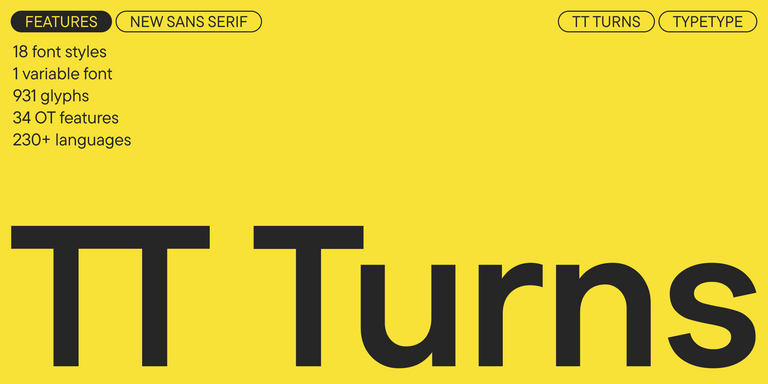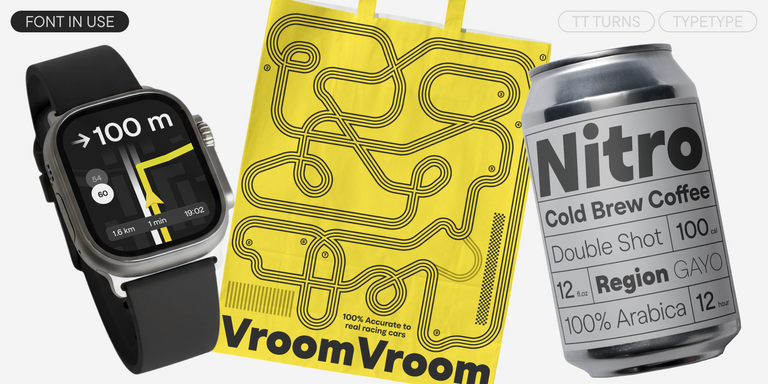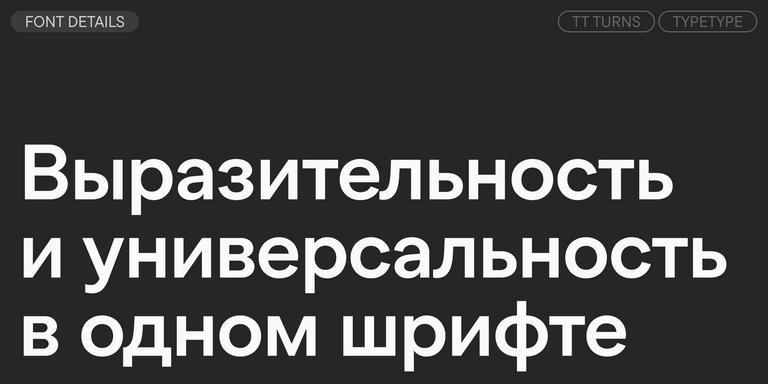
Музейные шрифты
TT Odellia — старостильная антиква с современным рисунком, вдохновлённая венецианскими шрифтами и классической музыкой.
TT Nooks Serif — акцидентная новостильная антиква с лёгким налётом эгоцентричности. У неё острый и твёрдый, при этом элегантный и статный характер.
TT Nooks Script — шрифт с уникальным рисунком, который не имеет прямых аналогов.
TT Qurdisma — узкий и плотный декоративный шрифт, напоминающий причудливое растение. Вьющиеся, плавные контуры рождают растительный орнамент.
TT Dott — экспериментальный пиксельный гротеск, в котором за основу пикселя взят круг. Это пластичный и необычный акцидентный шрифт, вызывающий ассоциации одновременно с вышивкой и техно-вечеринками.
TT Rationalist — функциональный и оригинальный брусковый шрифт с актуальным рисунком. Он универсален и подходит как для заголовков, так и для массивов текста.
TT Turns — геометрический гротеск с акцентными круглыми знаками и выразительными нависающими элементами. Это универсальный шрифт, который лаконично выглядит и отлично читается в маленьком размере, при этом в крупных кеглях становится акцидентным и проявляет свой характер на максимум. Он энергичный, сильный и динамичный — особенно отчётливо это проявляется в наклонных начертаниях.
TT Jenevers стилистически относится к голландским антиквам нового стиля. В гарнитуре присутствуют характерные детали, свойственные голландским антиквам — это ассиметричная форма засечек или нерегулярный наклон овалов.
TT Regins — шотландская новостильная антиква с королевским характером. Яркий контраст и острые треугольные засечки придают этому шрифту строгий и властный нрав.
TT Quaris — изысканная и современная ленточная антиква. Перед разработкой этой гарнитуры мы провели глубокое исследование архетипов ленточных антикв.
TT Ricordi Allegria — современная ленточная антиква, отличительные особенности которой, гиперболизированная разноширинность в пропорциях, контраст между штрихами, клиновидные окончания штрихов и отсутствие традиционных засечек.
TT Bakers — пластичная антиква с нежным и живым характером. Этот шрифт похож на свежую выпечку: он тёплый и мягкий, особенно в жирных начертаниях.
TT Modernoir — акцидентный гротеск с разноширинными пропорциями. Плавные линии и изящные формы ар-нуво в этом шрифте сочетаются с ритмичностью и импровизационной свободой джаза.
TT Moons — узкая и контрастная антиква. Данное шрифтовое семейство очень элегантно работает в классических темах дизайна. TT Moons по стилистике относится к глиптальным новостильным шрифтам. Идеальная сфера использования TT Moons — это верстка журналов, книг и газет.
TT Ricordi Greto — неконтрастный флорентийский гротеск с динамичными пропорциями. Это единственный гротеск среди антикв в коллекции TT Ricordi, при этом в нем сохранились едва заметные засечки, отсылающие к прототипу.
TT Firs Neue — скандинавский гротеск, сочетающий выразительные графические элементы с универсальностью использования. Мы проанализировали каждый контур и графический элемент. Пересобрали шрифт заново, чтобы сохранить лучшее и исправить необходимое.
TT Fellows — гуманистический гротеск с механистическими мотивами. Открытые формы, дружелюбно-нейтральный характер тонких весов и ещё более мягкий характер в жирных начертаниях.
TT Ramillas — стильная и современная антиква. Включает уникальные декоративные начертания и буквицы с цветочным орнаментом.
TT Gertika — геометрический гротеск с динамичным характером и танцующим ритмом. Идея шрифта зародилась из леттеринга на американском плакате второй половины 30-х годов.